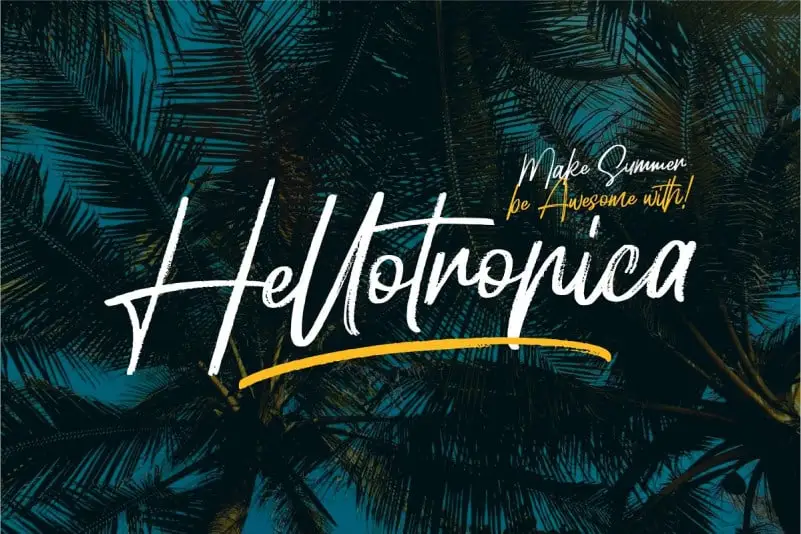
Hellotropica Handbrush Font – Download Grátis
Hellotropica Handbrush Font é uma escolha perfeita para aqueles buscando uma fonte que transmite a essência do verão com estilo elegante e versátil. Desenvolvida pelo Designer 0001themes, essa fonte de script vem repleta de detalhes precisos e fluidos, oferecendo um acabamento perfeito para logotipos, texturas personalizadas, títulos e cabeçalhos. Além disso, ela traz uma característica inovadora da Opentype que adiciona valor estético a seus produtos gráficos. Com o seu design inspirado nas artefatos de pinceladas naturais para o verão, Hellotropica Handbrush Font oferece um toque natural e único, perfeito para anúncios e materiais promocionais. Esta fonte não apenas é atraente visualmente, mas também adaptável às necessidades variadas do design. O swash que vem integrado nesta fonte pode ser utilizado em conjunto com outros designs para criar ambientes de logotipos impecáveis e produtos gráficos estilizados. Este projeto da 0001themes é uma excelente adição à sua coleção de recursos gráficos, especialmente se você está buscando algo que transmita a atmosfera do verão em um toque elegante.